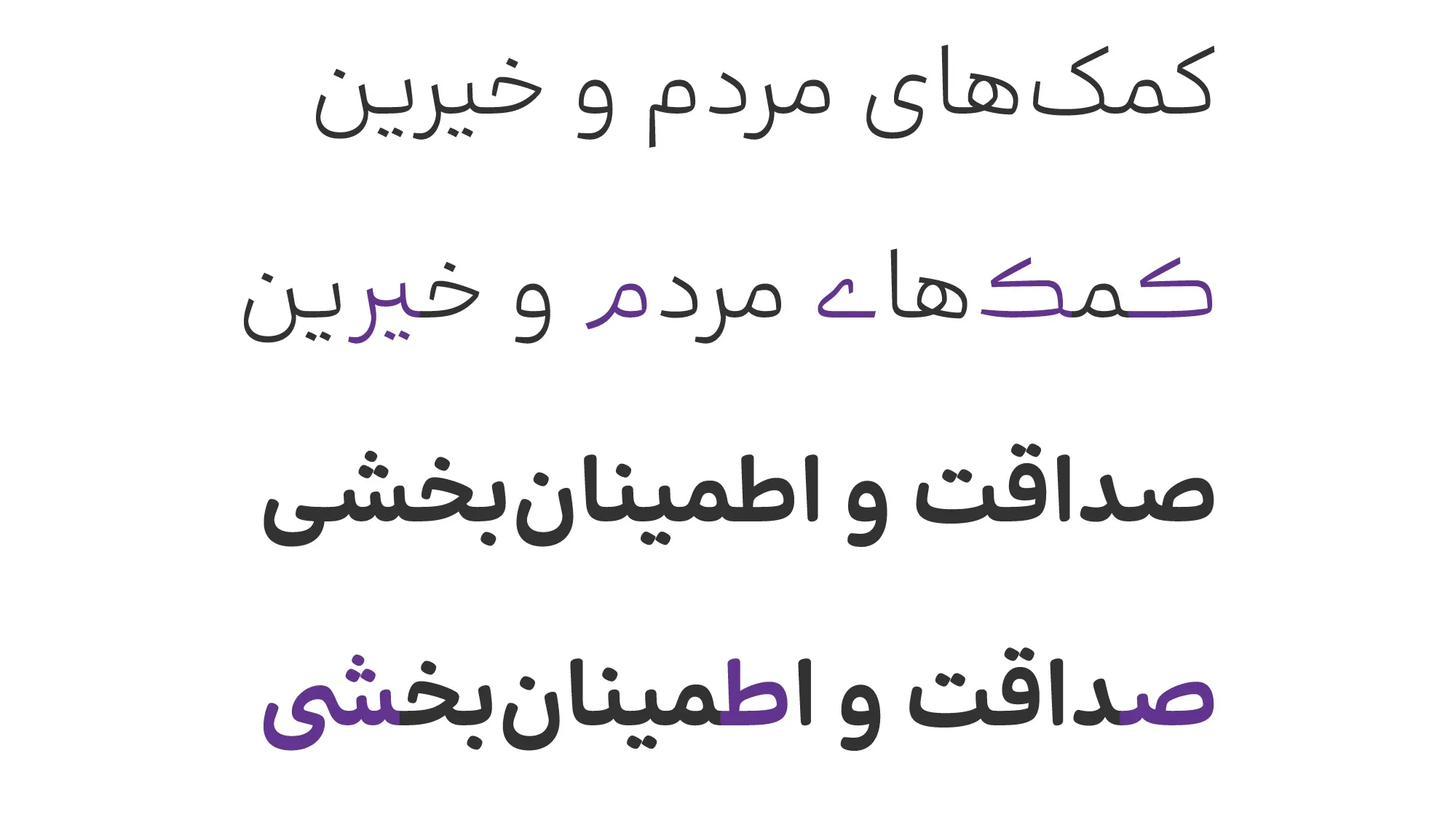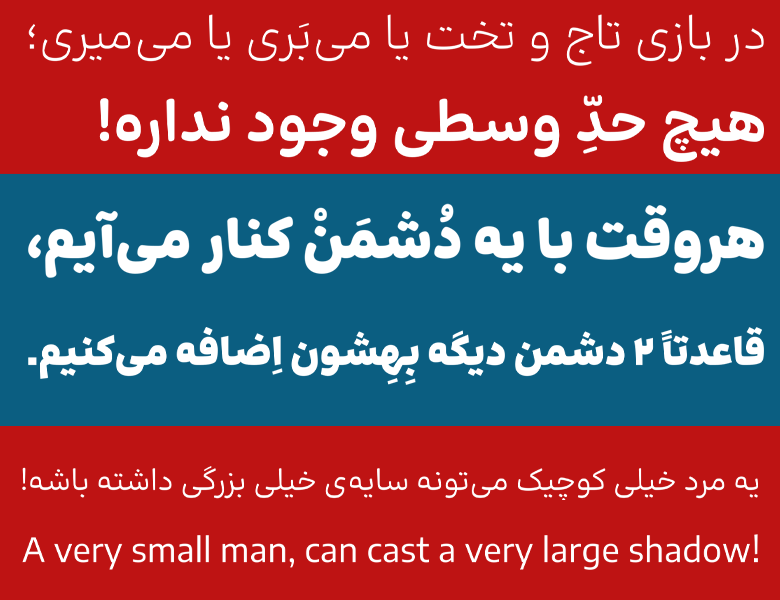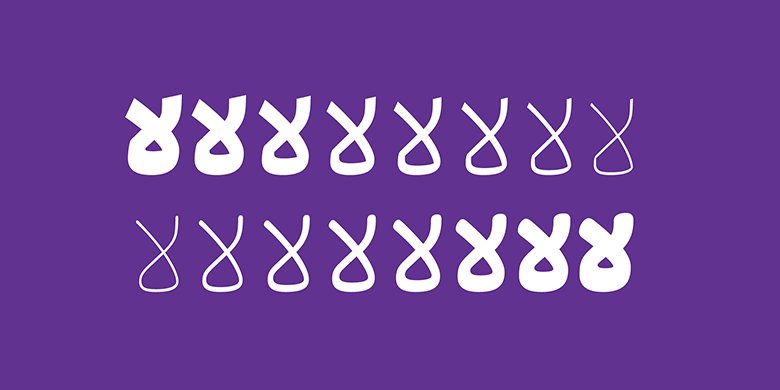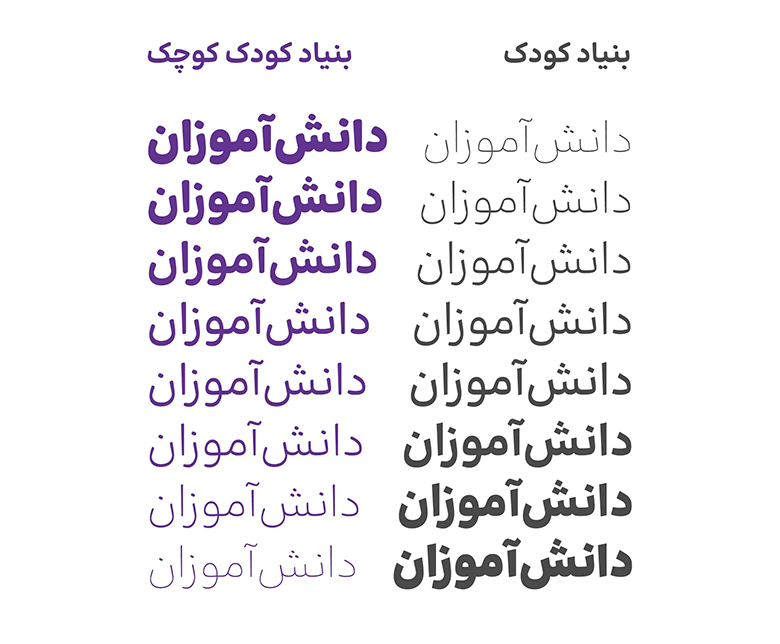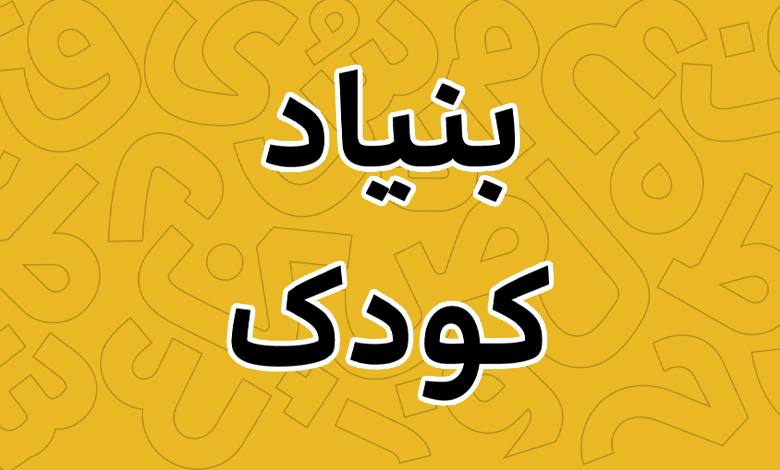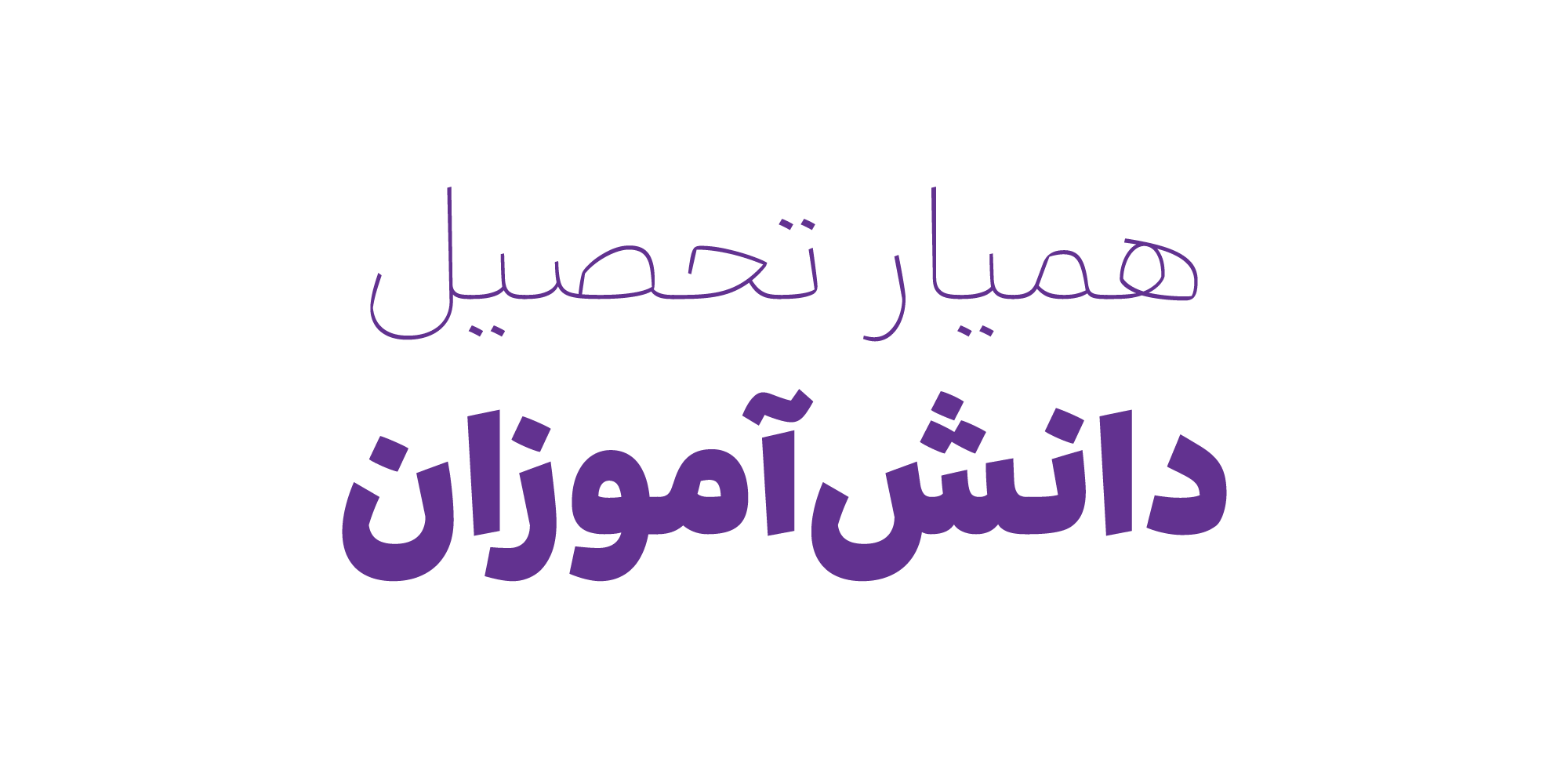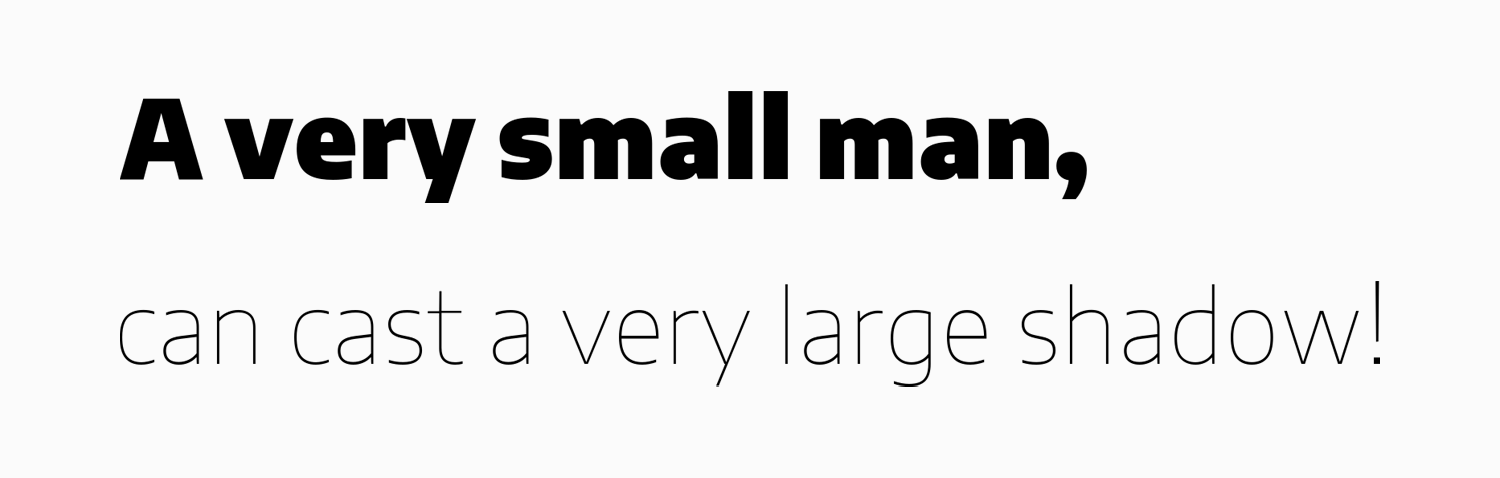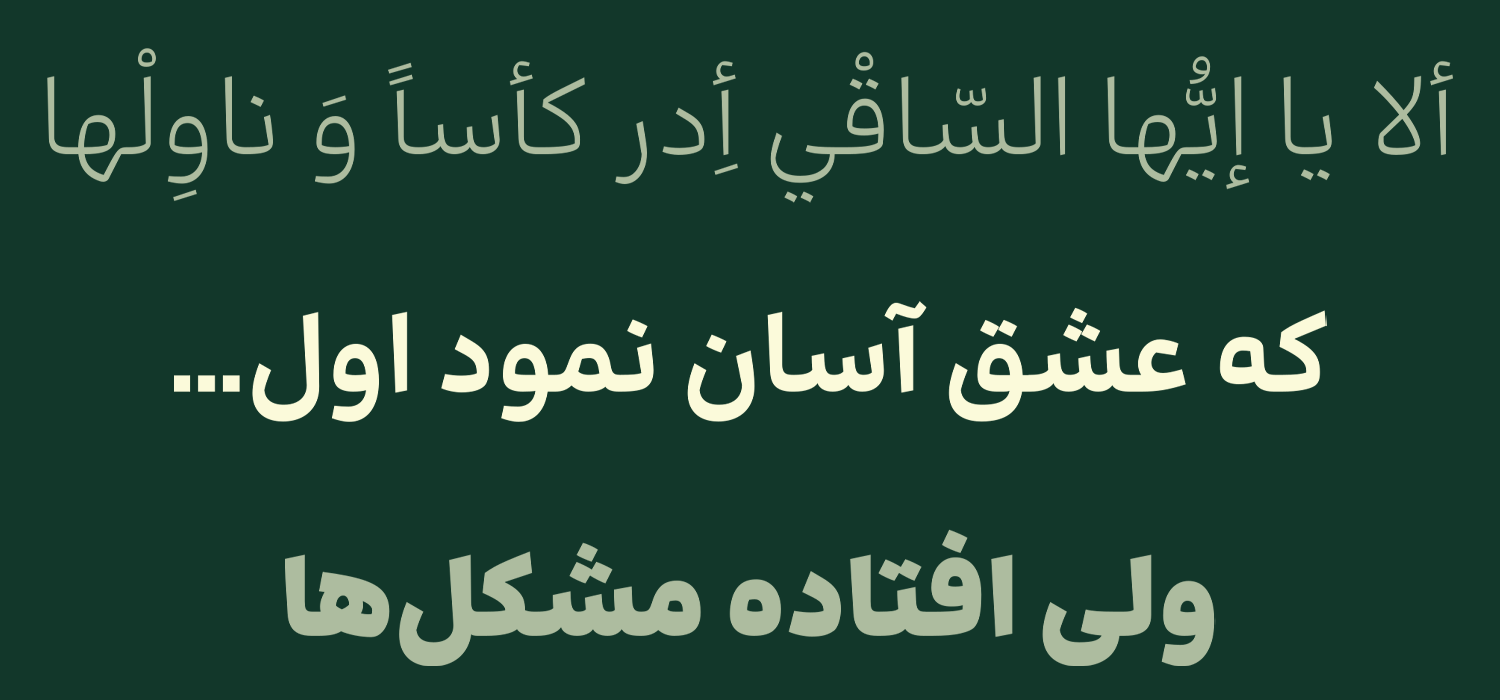
فونت بنیاد کودک (BonyadeKoodak)
فونت بنیاد کودک (به انگلیسی: bonyadekoodak) از سری فونت‌های مناسب متن است که بر اساس خط نسخ توسط رضا بختیاری فرد طراحی و مهدی ارشادی توسعه نرم‌افزاری آن را انجام داده است. این فونت کاملا خودمانی و بی آلایش است و از آن می‌توانید برای متن‌های بلند، عناوین و تبلیغات استفاده کنید. فونت بنیاد کودک رایگان نبوده و با تنوع وزنی ۸ گانه که در دو سبک دارد، قابل خرید در سه بسته مختلف است.
این فونت دارای فرمی کاملا ساده، با چشمی‌های نسبتا بزرگ و دندانه‌هایی کاملا واضح است که در کنار پشتیبانی از چند نوع سبک استایل و همچنین وزن‌های متعدد، از نظر خوانایی بسیار عالی بوده و برای استفاده در متن‌های طولانی بسیار کاربردی است.
در ادامه این این نوشته از فونتچی به نقد و بررسی کامل فونت بنیاد کودک می‌پردازیم؛ قلمی که با رعایت منحنی‌ها در اطلاق خطوط صاف و موازی کاملا خوب عمل کرده و به همین جهت می‌تواند بازه بزرگی را برای خواندن متون بلند فراهم کند.
بررسی و دانلود فونت بنیاد کودک (BonyadeKoodak)
پیش از اینکه به معرفی فونت بنیاد کودک بپردازیم بد نیست بدانید که نام این فونت برگرفته از بنیادی به همین نام است که در راستای مسئولیت‌های اجتماعی روی «تامین نیازهای تحصیلی دانش‌آموزان کم‌برخوردار» فعالیت دارد. این فونت در سال ۱۴۰۱ برای این بنیاد به صورت اختصاصی تولید شده بود.
از همین جهت؛ بنیاد کودک در راستای تامین نیازهای دانش‌آموزان تصمیم گرفته فونت اختصاصی خود را به صورت عمومی منتشر کند. تیم طراحی نیز با این تصمیم همراه شد و سبک «کوچک» را طراحی کرد و به مجموعه افزود تا خانواده‌ی فونت برای عرضه‌ی عمومی جامع‌تر و کاربردی‌تر باشد و بتواند نیازهای بیش‌تری را پوشش دهد.
استایل و وزن فونت بنیاد کودک
فونت بنیاد کودک رایگان یک قلم خانواده‌دار است؛ از یک سبک گرد Rounded که با نام «کودک کوچک» نام‌گذاری شده، ساختاری کودکانه و شیرین را خلق کرده است که برای استفاده در رسانه‌های چاپی، دیجیتال و محیطی قابل استفاده و قابل اعتماد است. نسخه معمولی فونت هم در نوشته‌های بلند خوانایی خود را از دست نمی‌دهد و در تیترهای بزرگ دلبری می‌کند.
فونت رایگان بنیاد کودک دارای چندین ۸ وزن مختلف است که از نسخه Thin آغاز شده و تا نسخه Black می‌توانید از آن استفاده کنید. وزن‌های متنوع این فونت از نسخه نازک گرفته تا پهن، به شکل‌دهی و فرم‌دهی پروژه شما کمک کرده و باعث می‌شود که بتوانید روی کلمات کلیدی و تاکیدی، اصرار ورزید.
در نتیجه نمایش این نوع کلمات بهتر در دید مخاطب قرار گرفته و ارتباط بیشتری را با آن برقرار خواهد کرد که از همین جهت می‌تواند روی بازاریابی و فروش شما در هر حوزه‌ای که از این فونت استفاده می‌کنید موثر واقع گردد. خصوصا اینکه این فونت دارای سبک طراحی گرد در نسخه «فونت کودک کوچک» نیز می‌باشد.
پشتیبانی از چند زبان مختلف
فونت فارسی بنیاد کودک محدود به این زبان نیست و از آنجا که رسم خط عربی با زبان فارسی یکسان بوده و تنها تفاوت‌هایی جزئی در برخی حروف دارد، برای زبان عربی نیز می‌توانید از این فونت استفاده کنید. پشتیبانی این فونت در هر دو سبک بنیاد کوچک و معمولی کامل بوده و شامل حروف و تعداد می‌باشد.
فونت بنیاد کودک در نسخه عربی و فارسی دارای پشتیبانی کاملی از اعراب بوده و تمامی اعراب اصلی و تنوین‌ها در هم‌نشینی درستی با سایر اعراب «همزه، تشدید، سکون» قرار دارند که موجب به‌هم ریختگی کلمات یا چسبیدن برخی حروف به حروف قبل یا بعد خود نخواهد شد.
از نسخه ۲.۲ فونت بنیاد کودک که در بهمن ۱۴۰۲ آپدیت شده است، امکان پشتیبانی از زبان‌های کوردی و اردو نیز به این قلم افزوده شده است. علاوه بر اینکه کلیه حروف متفاوت با زبان فارسی دارای یونیکد اختصاصی خود هستند، اعراب گذاری بر روی برخی حروف و استفاده از سمبل‌های تزئینی روی آنها نیز افزوده شده است که در این دو زبان بسیار مورد استفاده قرار می‌گیرد.
در کلیه زبان‌های عربی، اردو و کوردی نیز کلیه حروف متفاوت با رسم‌خط فارسی مانند «ک، ی، ه، ؤ، ئ» در زبان عربی یا «ﮧ، ﮩ، ے» در زبان اردو، دارای لیگچرهای اختصاصی خود بر اساس استاندارد یونیکد هستند. همچنین از حروف متفاوت در زبان اردو، به عنوان حروف جایگزین در سایر زبان‌ها می‌توان استفاده کرد.
با دانلود فونت بنیاد کودک برای فتوشاپ می‌توانید از طریق تنظیمات اپن‌تایپ به تمام گلیف‌های این قلم دسترسی داشته و ضمن استفاده از حروف جایگزین، از امکان انتخاب فرمت اعداد فارسی یا عربی در کنار گلیف‌های تزئینی که پشتیبانی می‌کند استفاده نمایید.
همچنین این فونت از زبان انگلیسی پشتیبانی کاملی دارد و همان ساختاری که برای زبان فارسی روی فونت پیاده سازی شده برای آن درنظر گرفته شده است. در نسخه انگلیسی فونت از فونت دیگری وام گرفته نشده و کلیه حروف و سایر کاراکترهای زبان لاتین دارای طراحی اختصاصی هستند.
دارای حروف و ترکیبات جایگزین فارسی و عربی